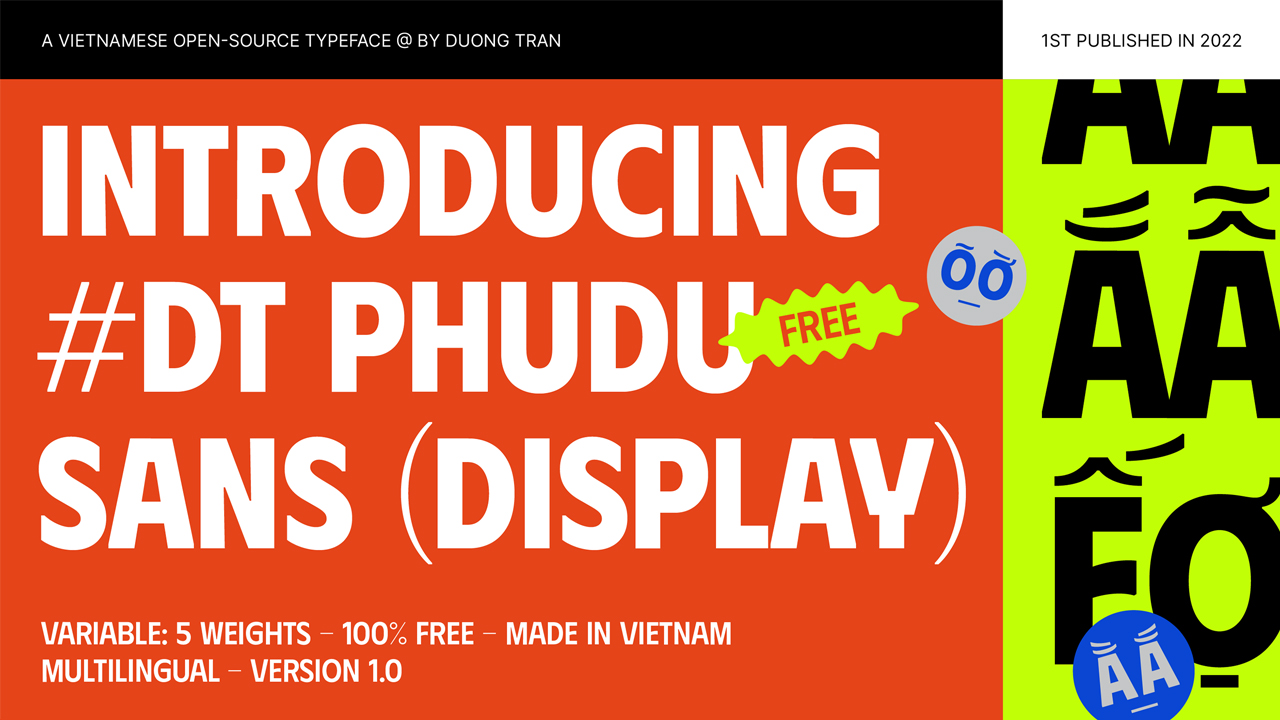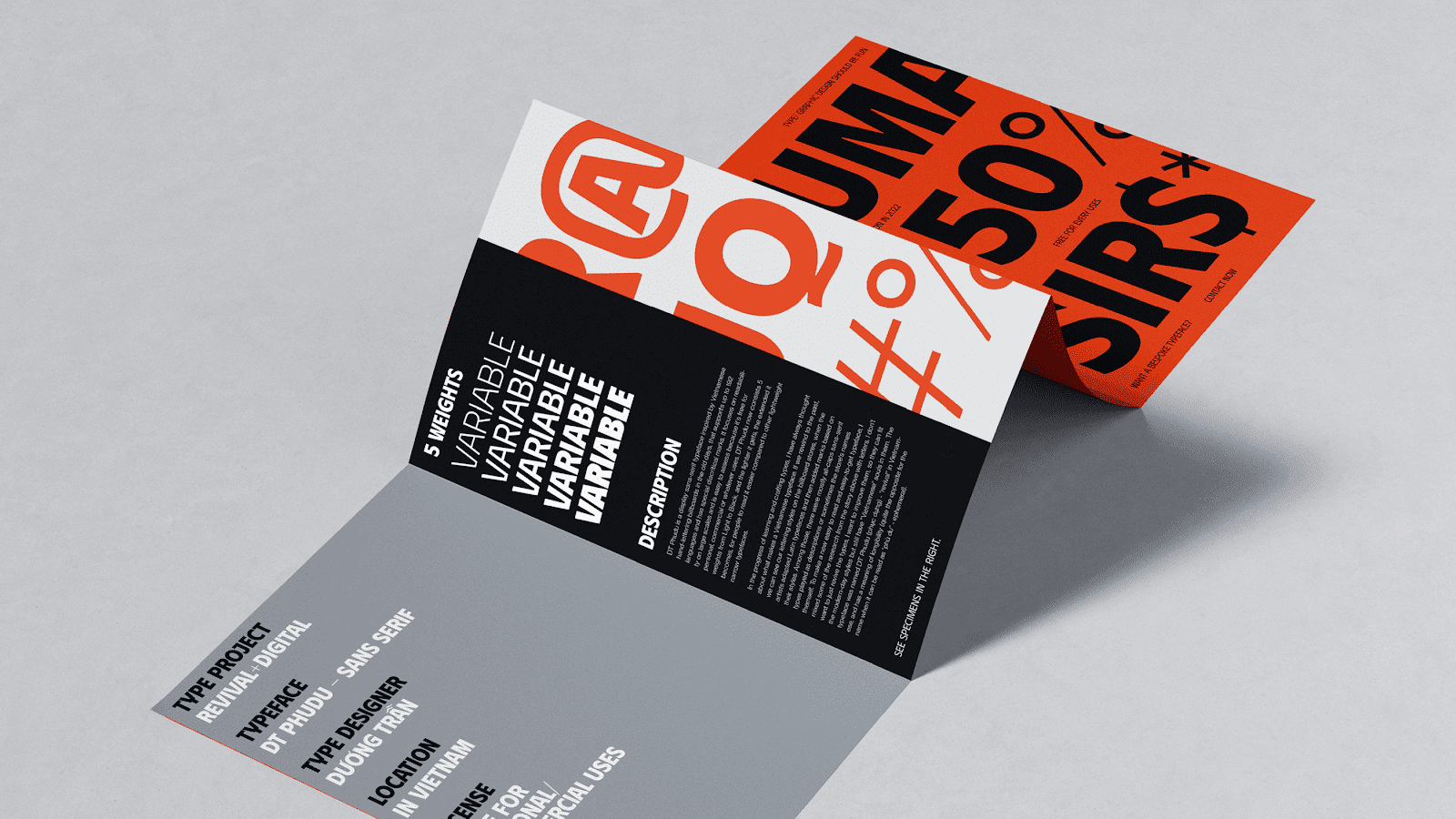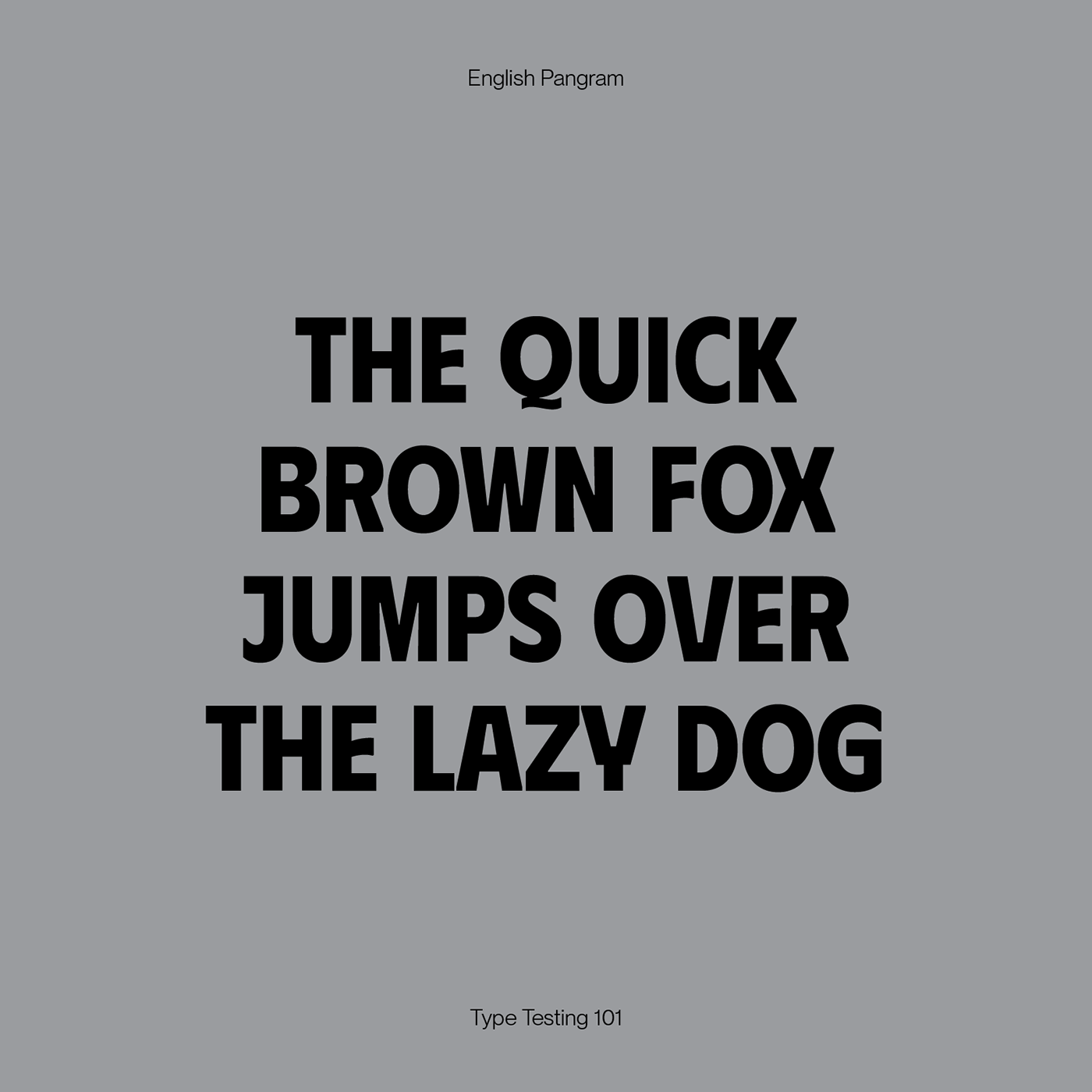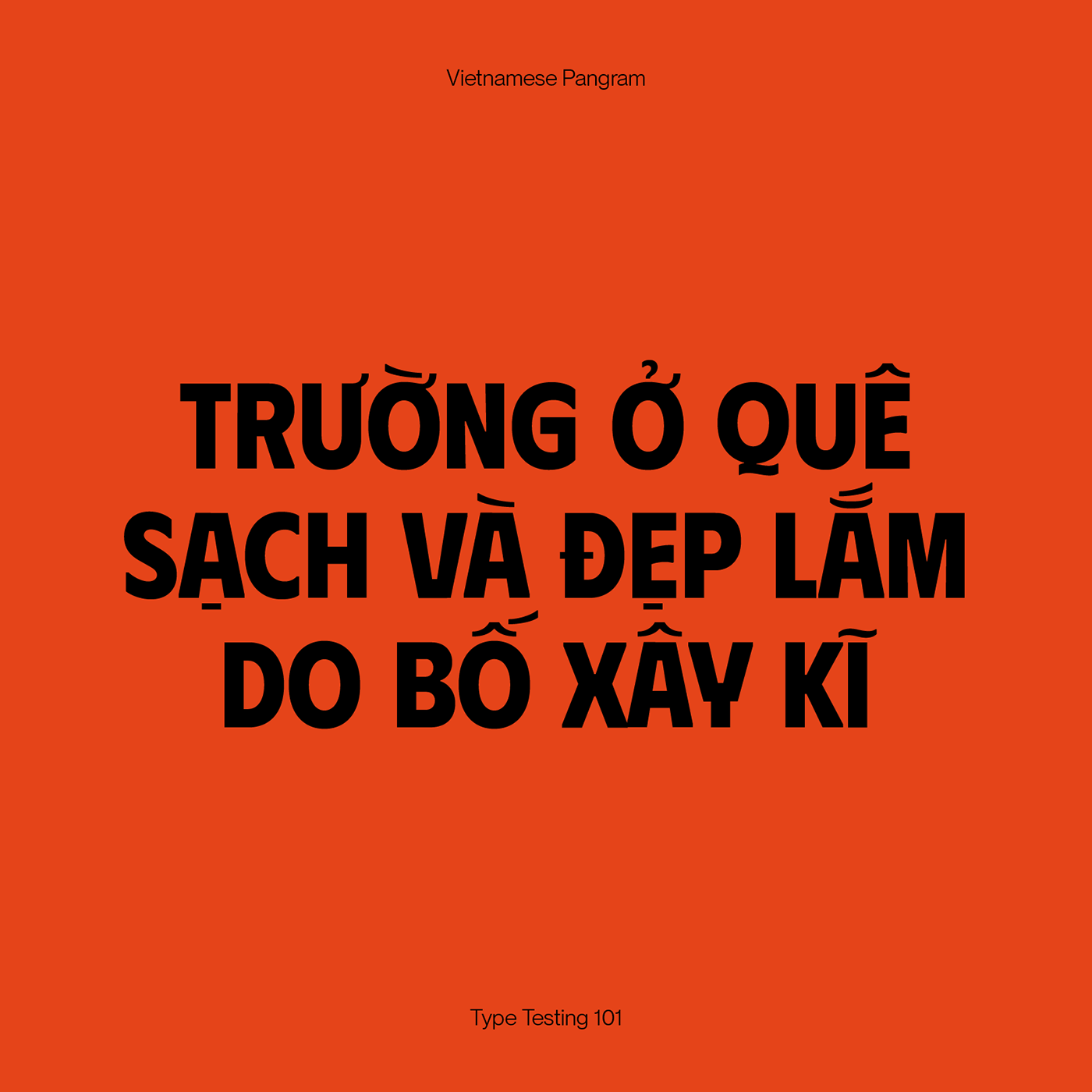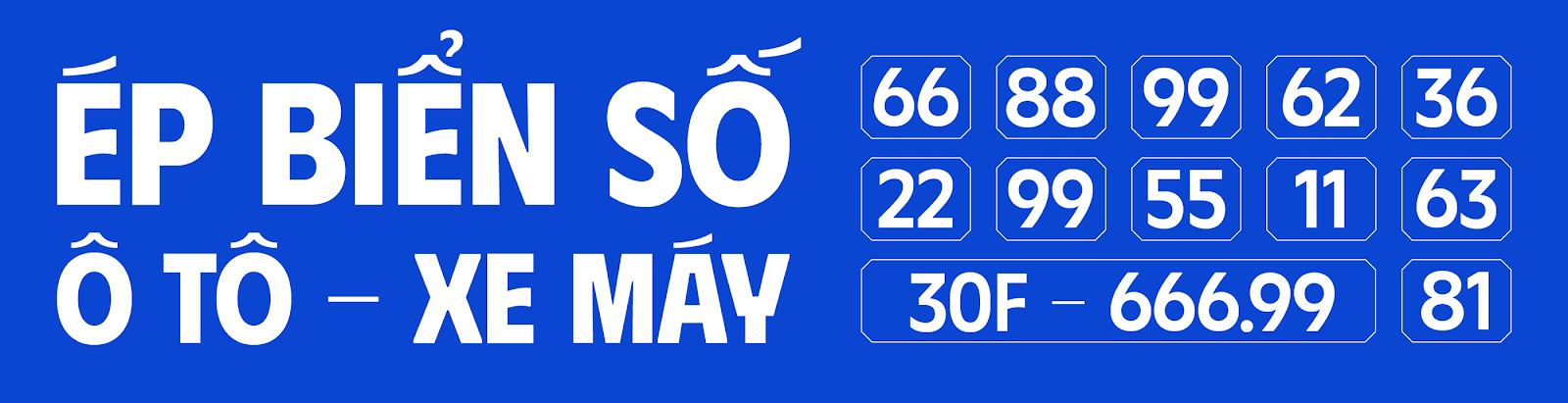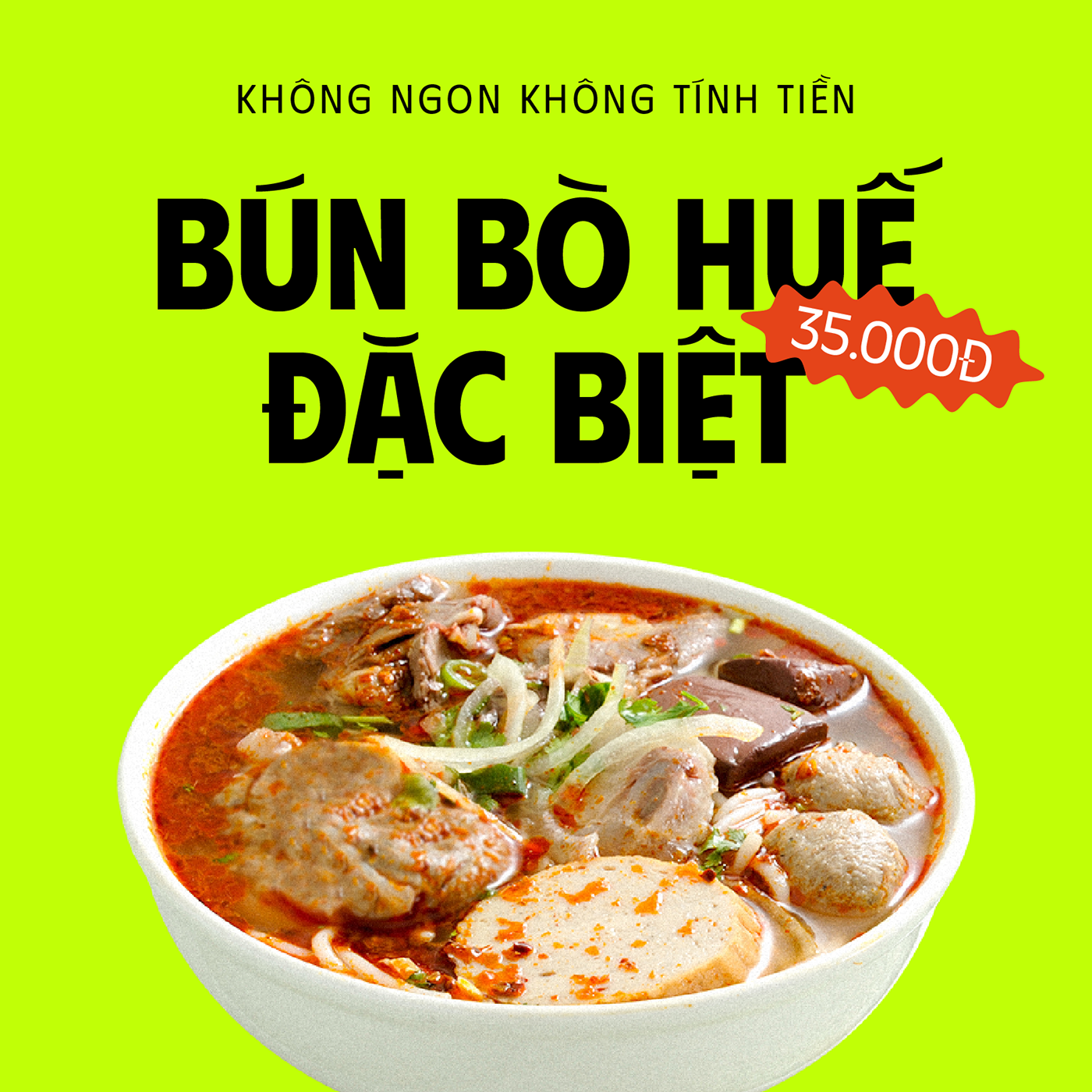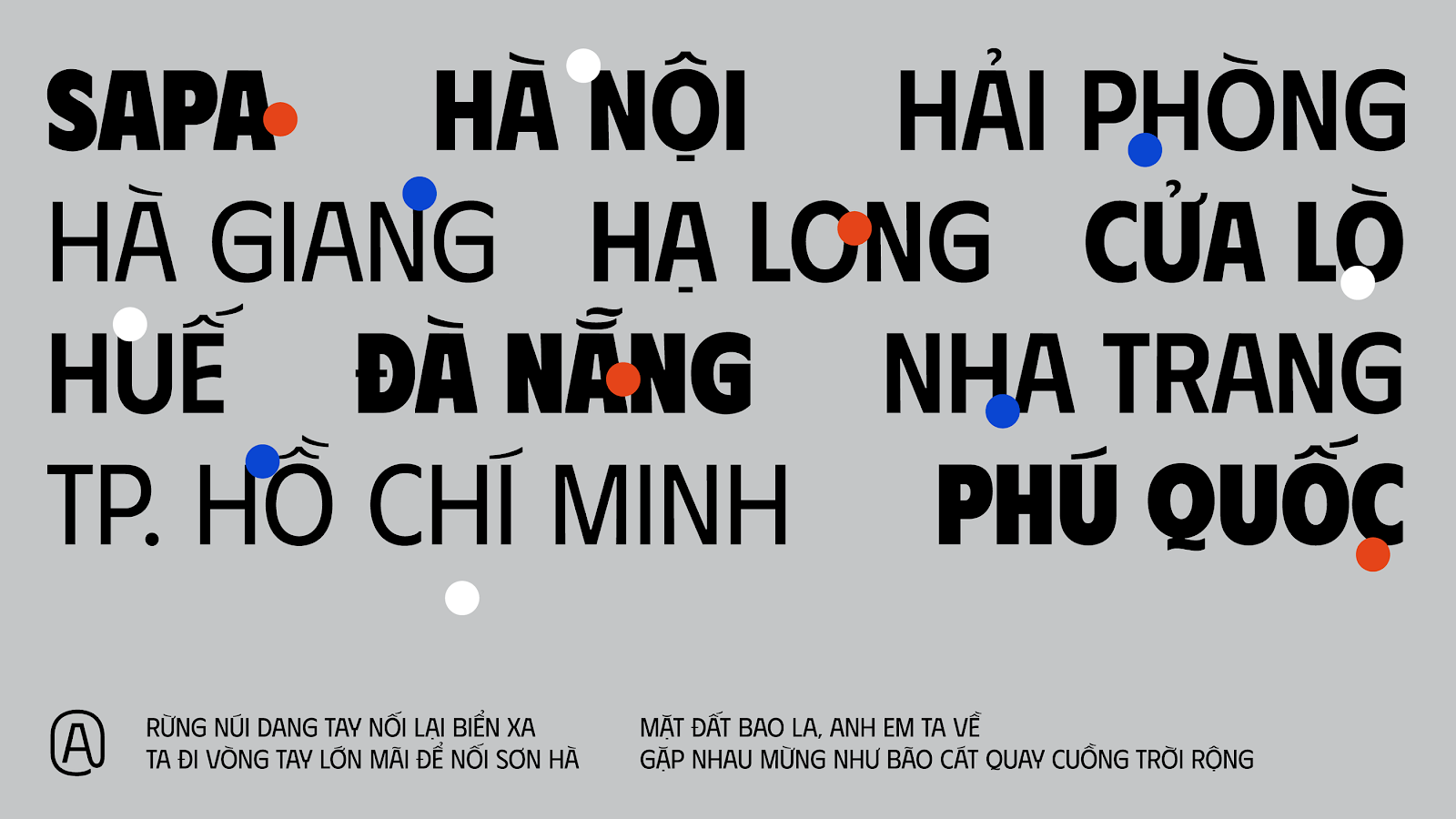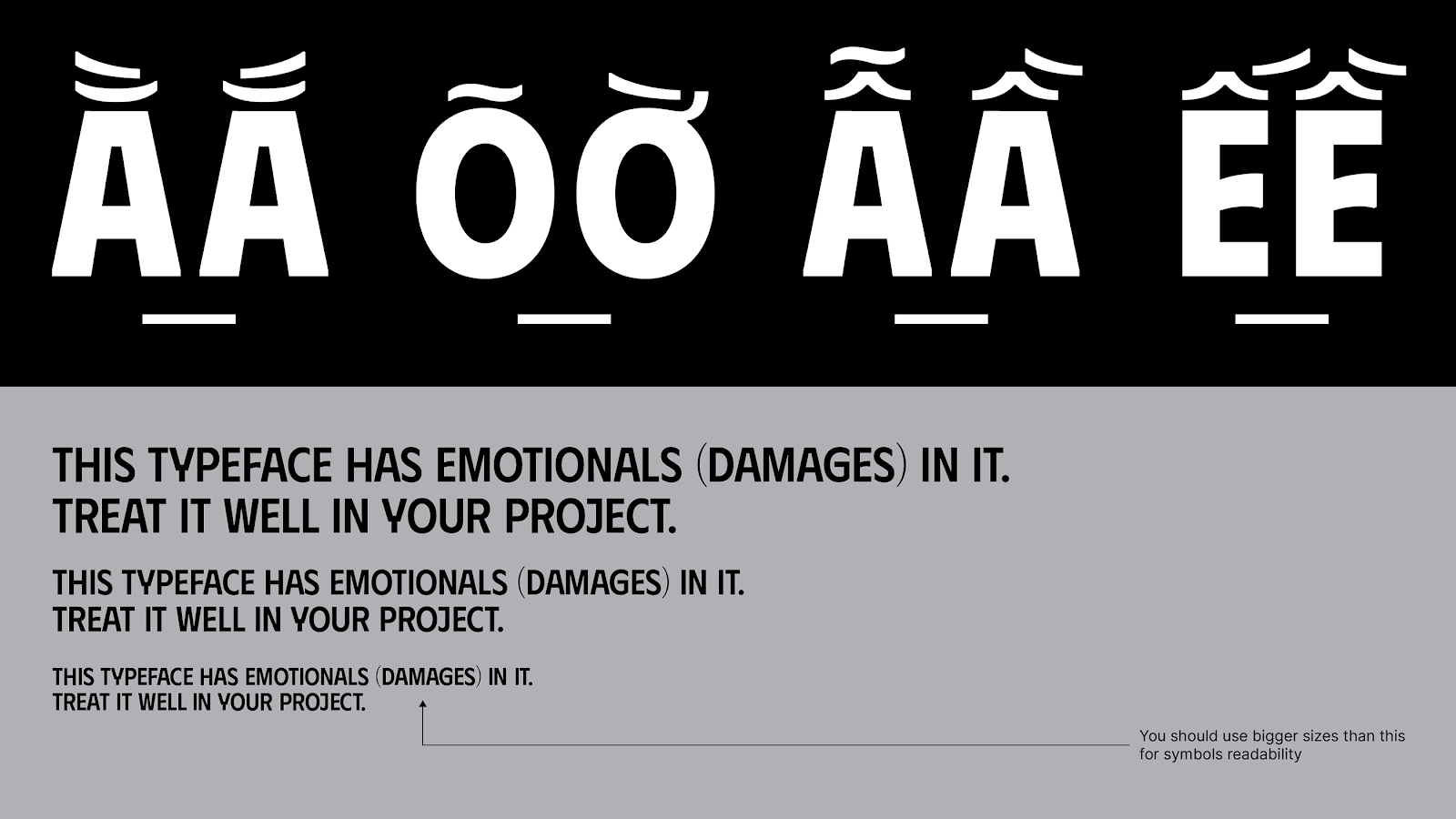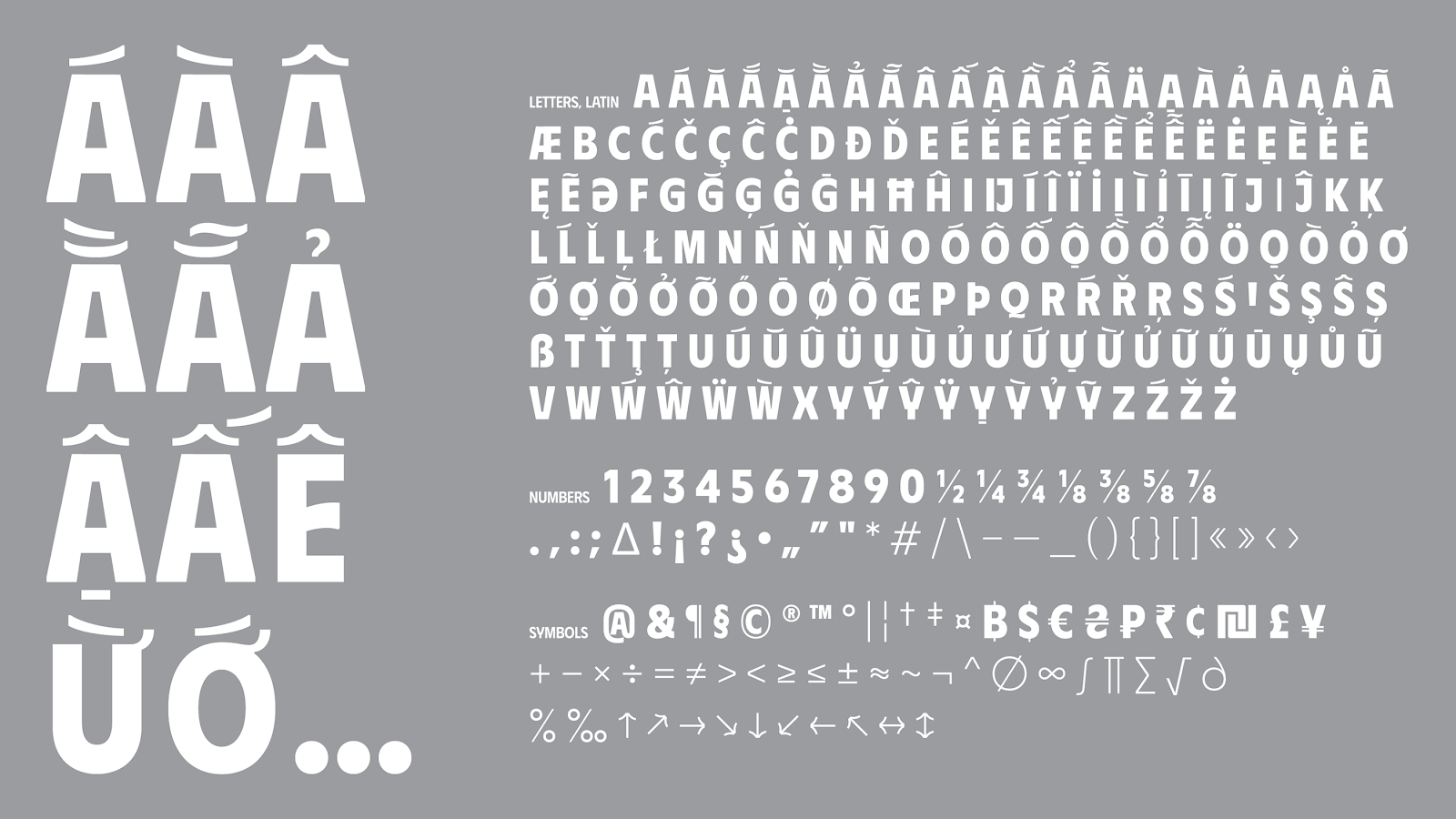
Font DT Phudu – Font chữ phong cách xưa cũ
Font DT Phudu một font chữ tiếng Việt phát triển bởi Duong Tran, font được lấy cảm hứng từ bảng quảng cáo chữ viết tay của Việt Nam ngày xưa, hỗ trợ tới 192 ngôn ngữ và có dấu phụ đặc biệt. DT Phudu bao gồm 5 kiểu từ Light đến Black. Bạn có thể sử dụng font chữ cho tiêu đề hoặc văn bản cũng như dễ dàng áp dụng cho bất kỳ thiết kế nào.
Tuy được lấy cảm hứng từ những thiết kế bảng hiệu xưa cũ nhưng font cũng được cải tiến cho phù hợp với phong cách hiện đại nhưng vẫn có hồn Việt. Kiểu chữ này được đặt trên là DT Phudu (phục dựng) – “phục hưng” trong tiếng Việt, có nghĩa là vượt thời gian (hoàn toàn trái ngược với tên khi nó có thể được đọc là “phù du”).